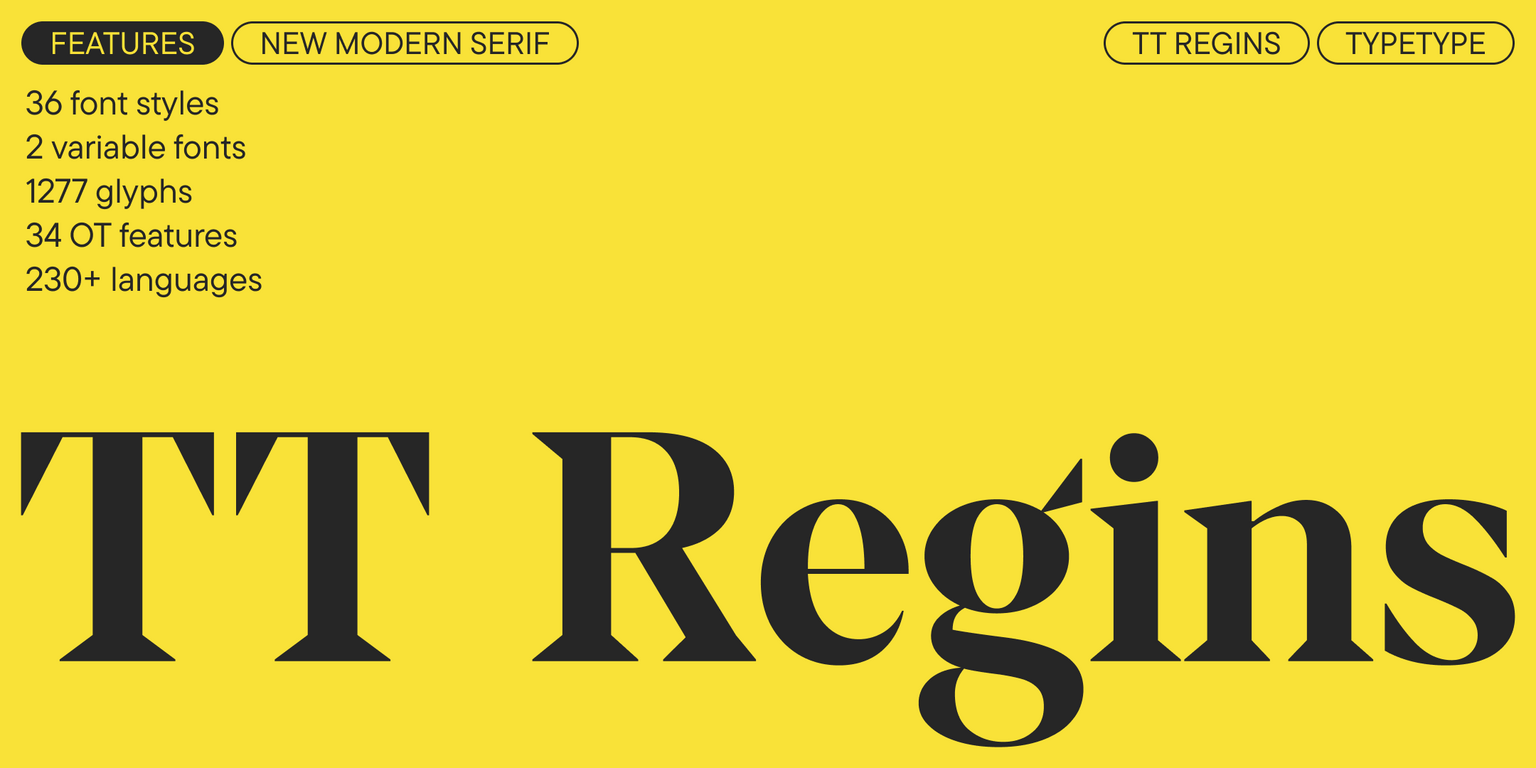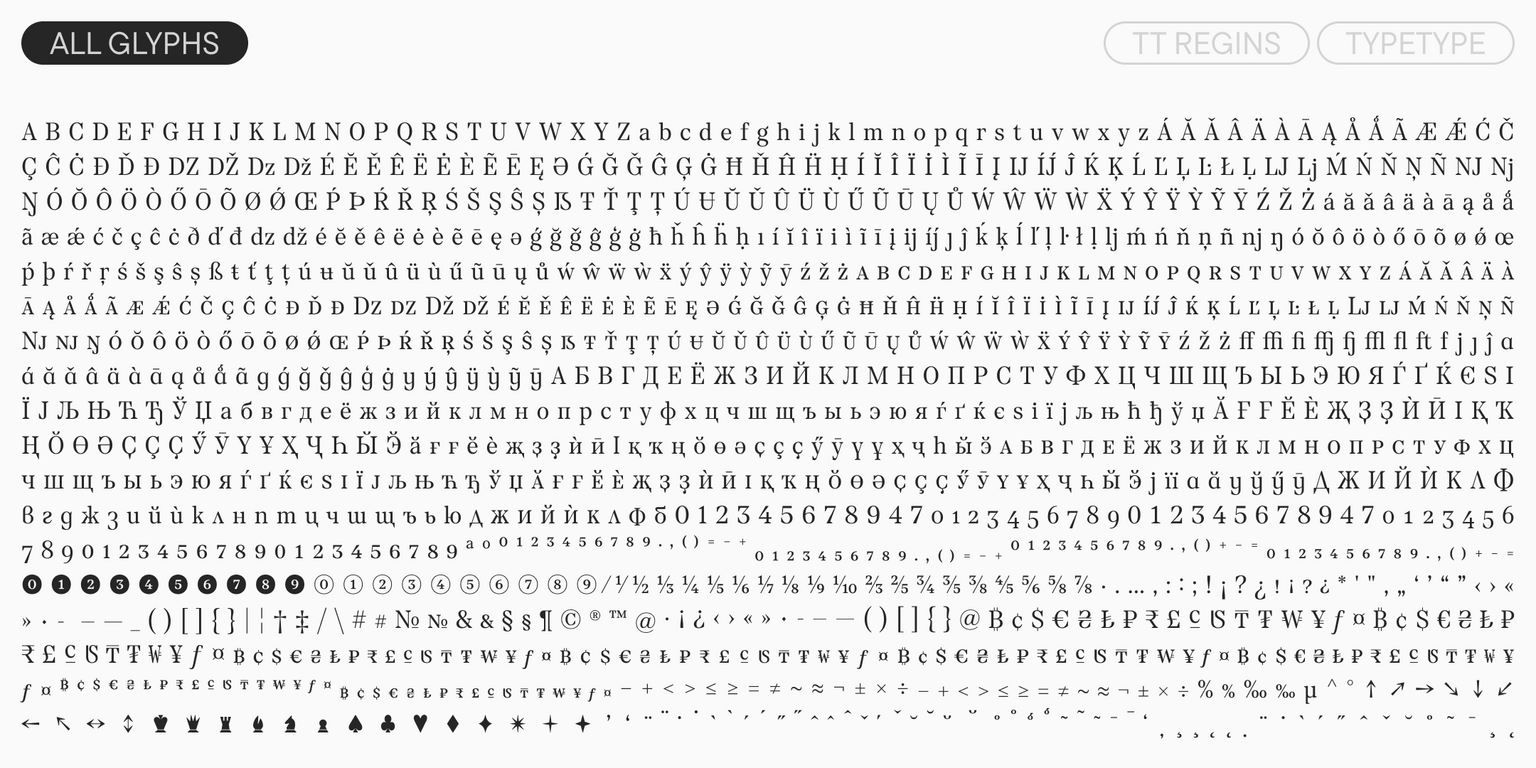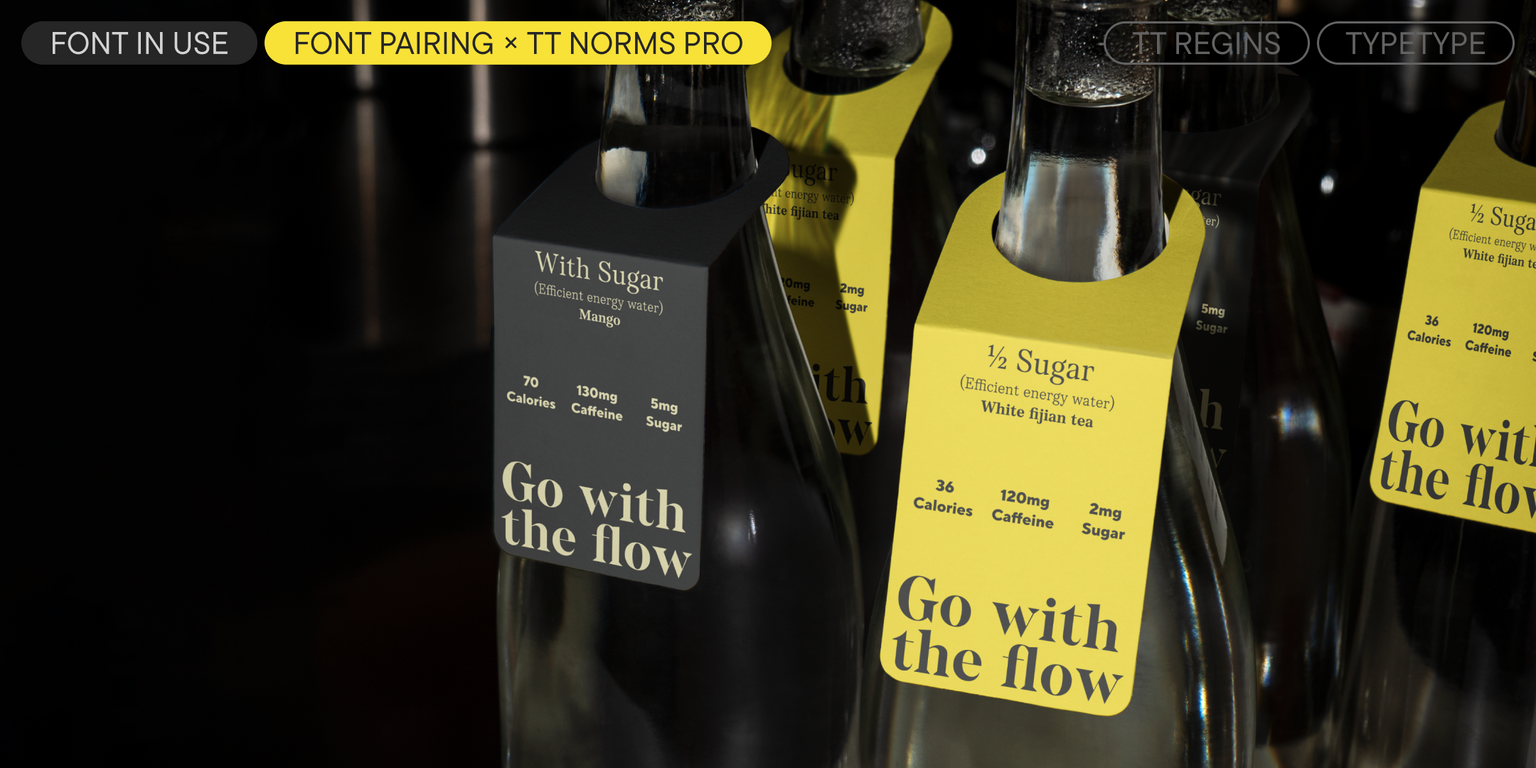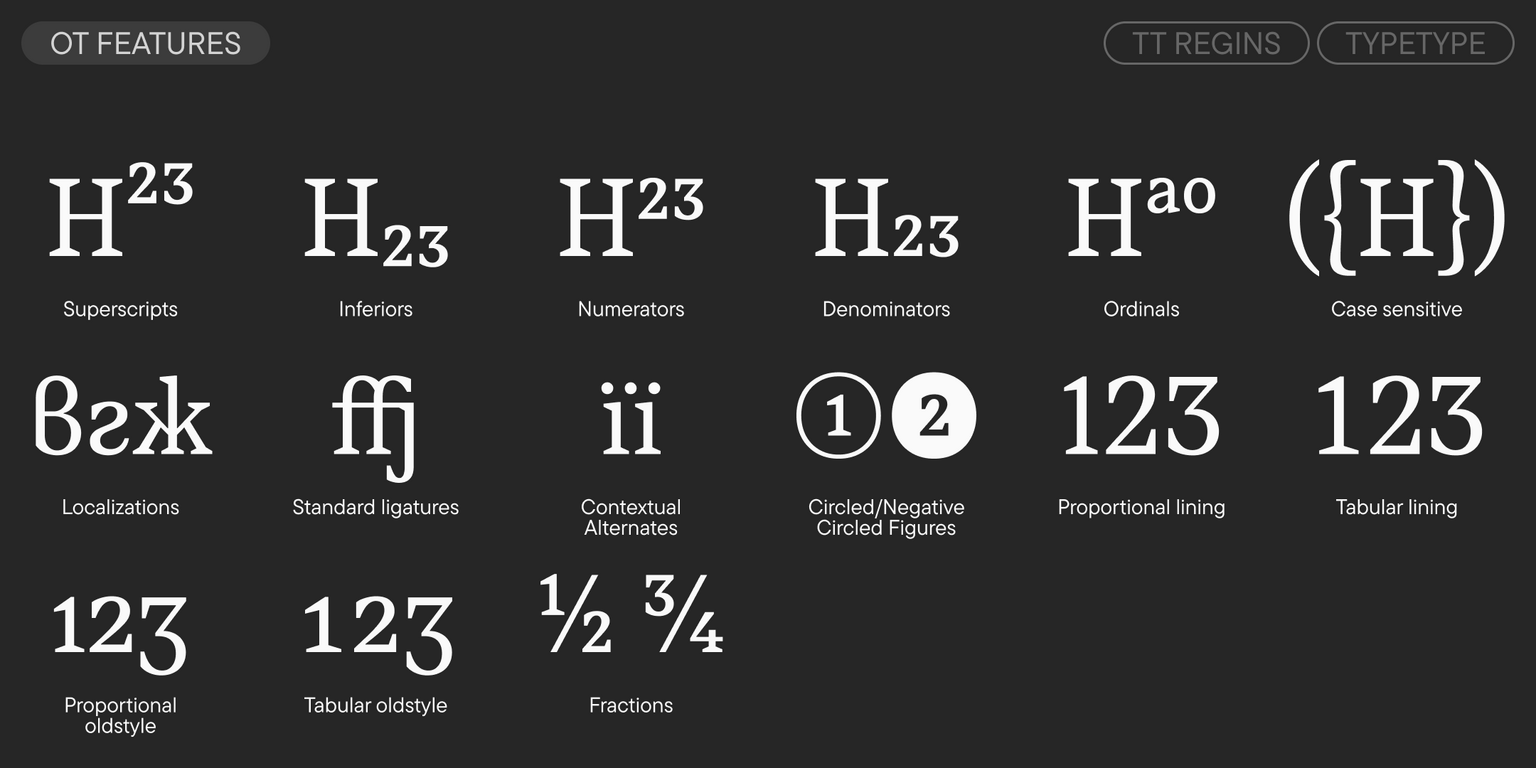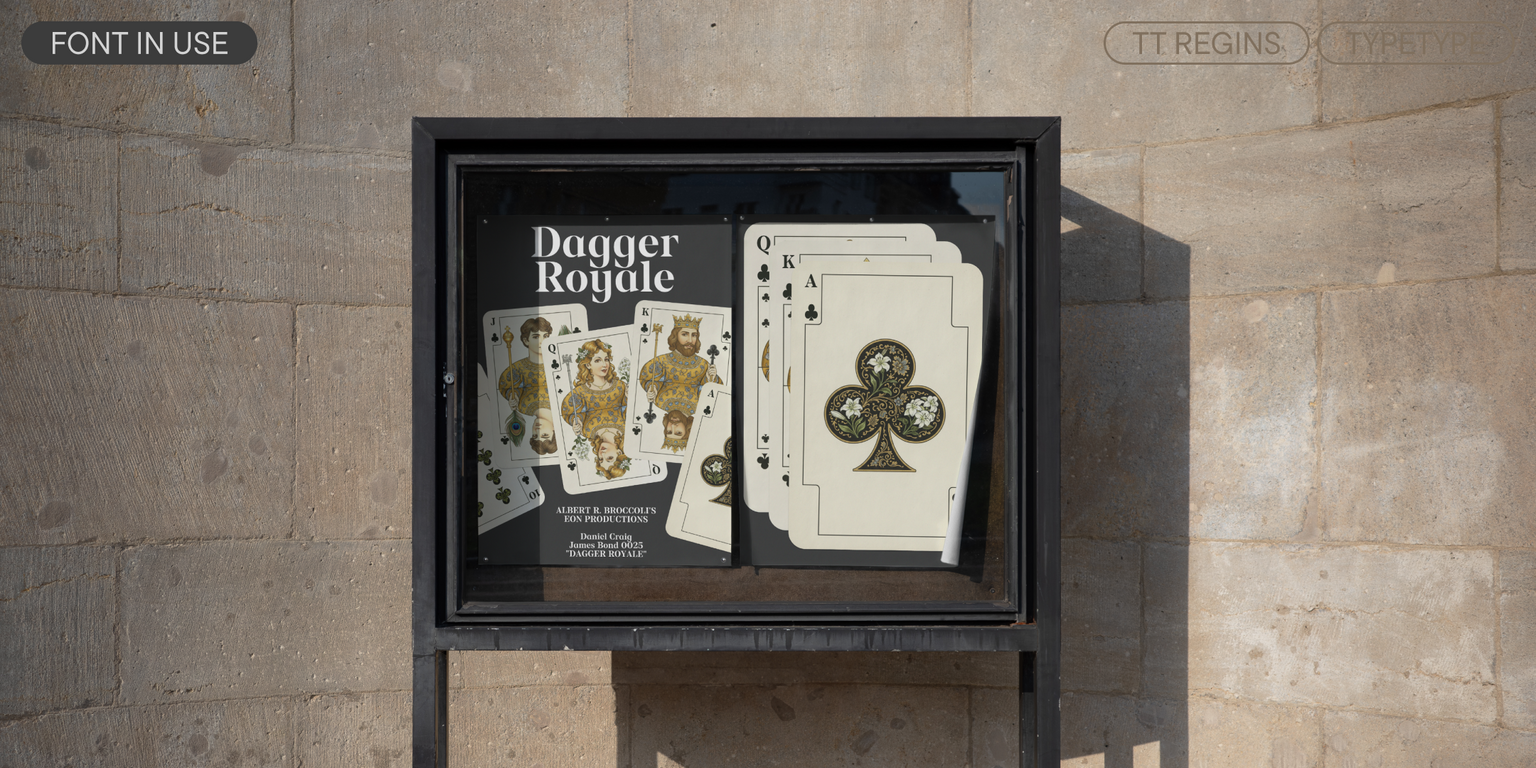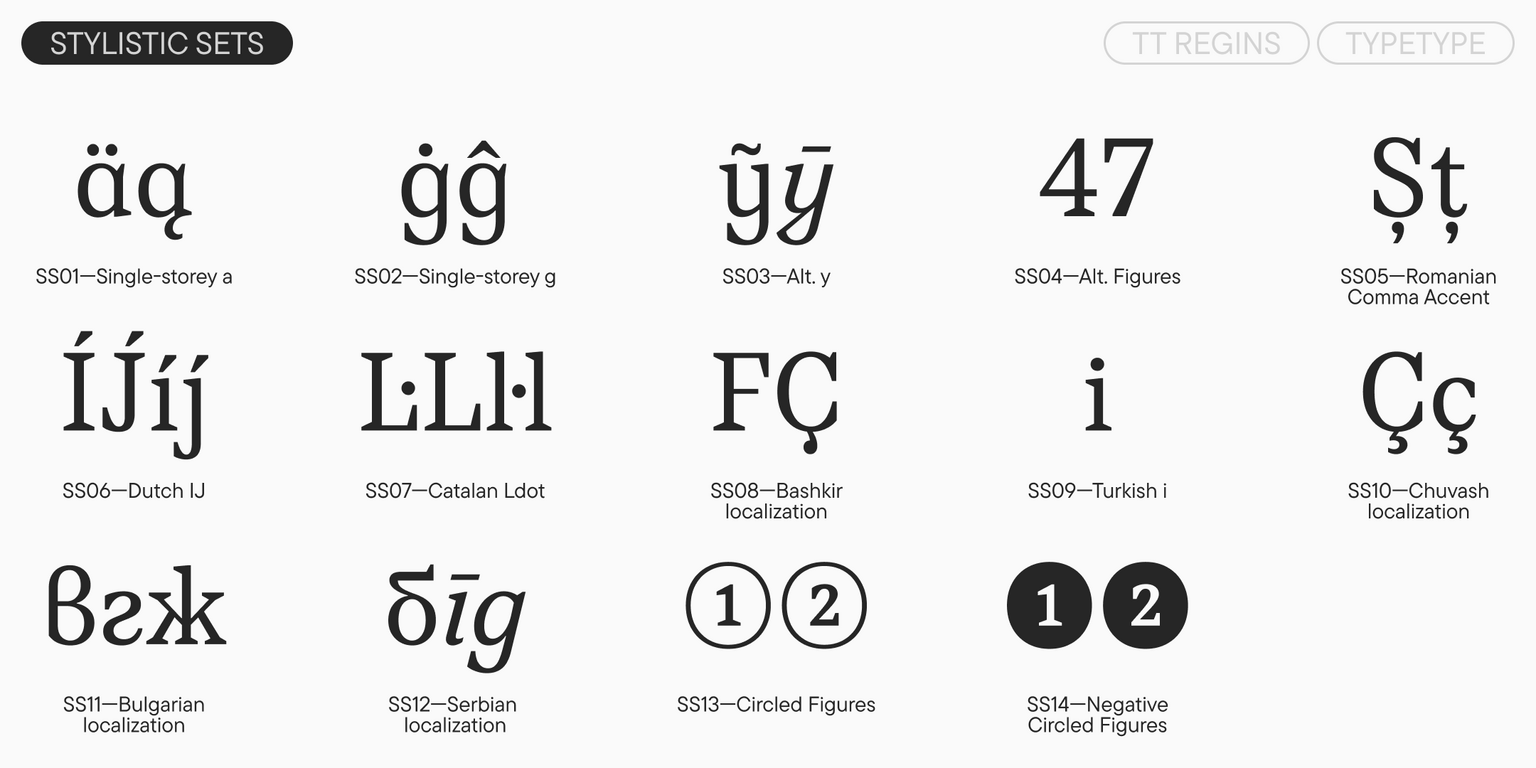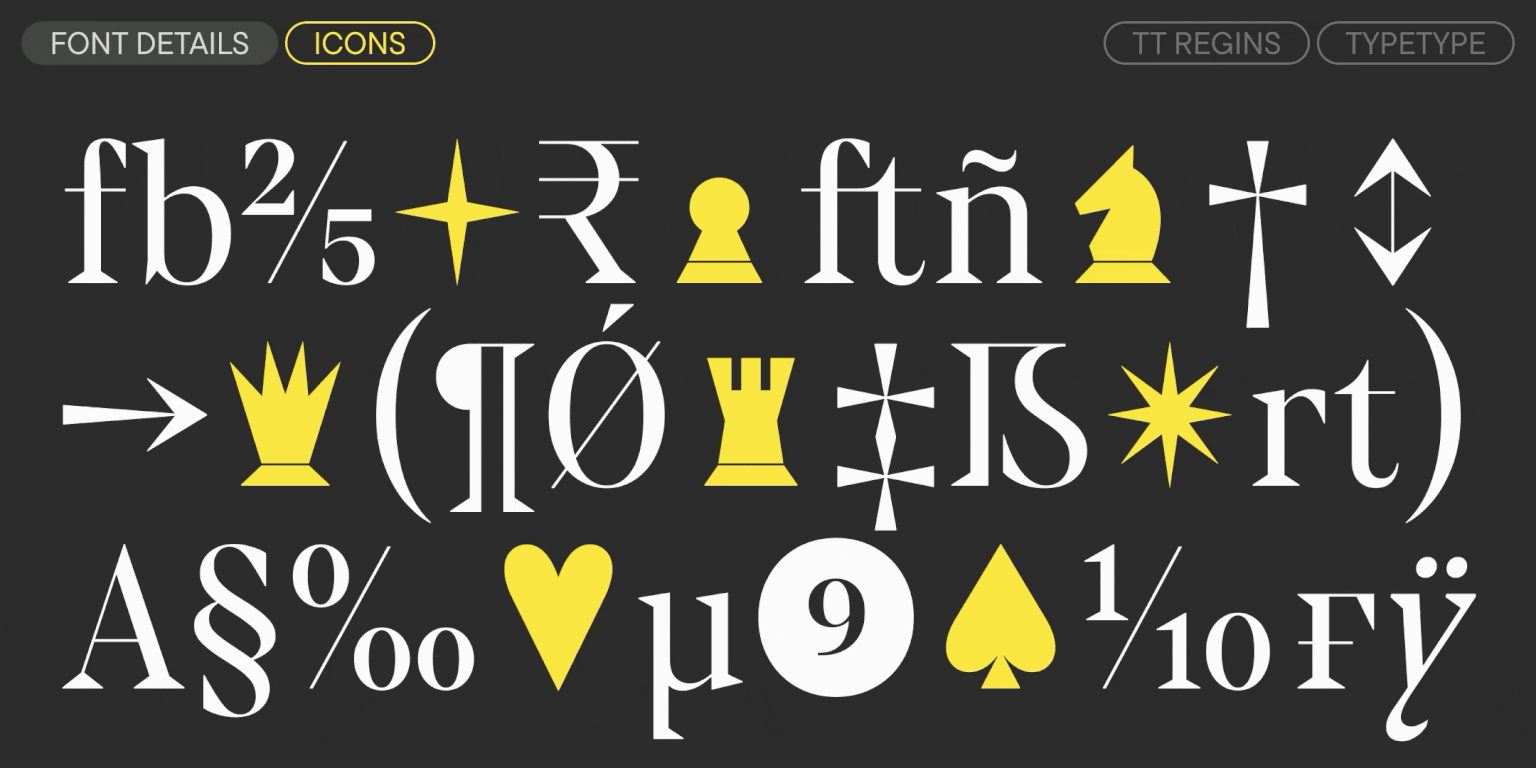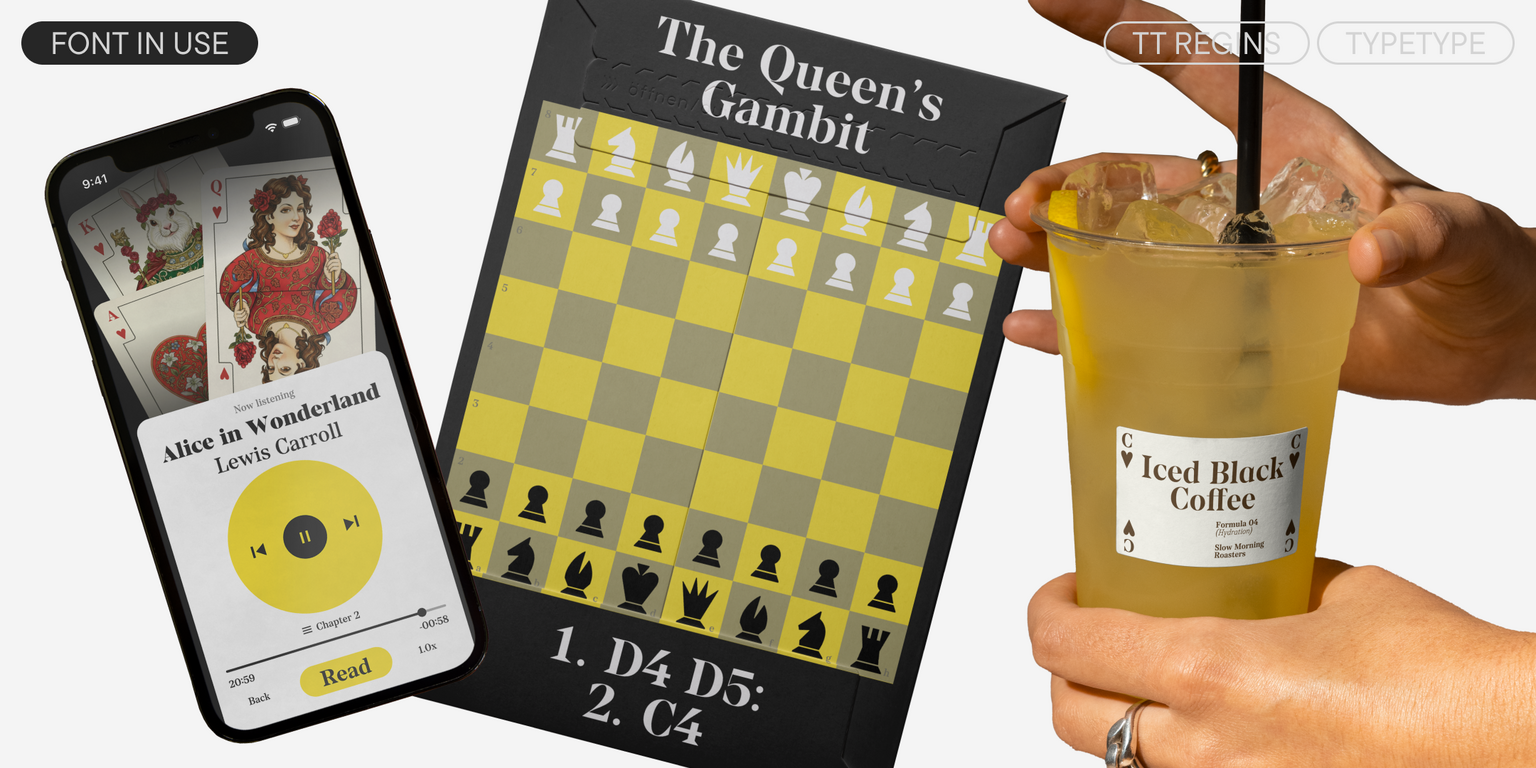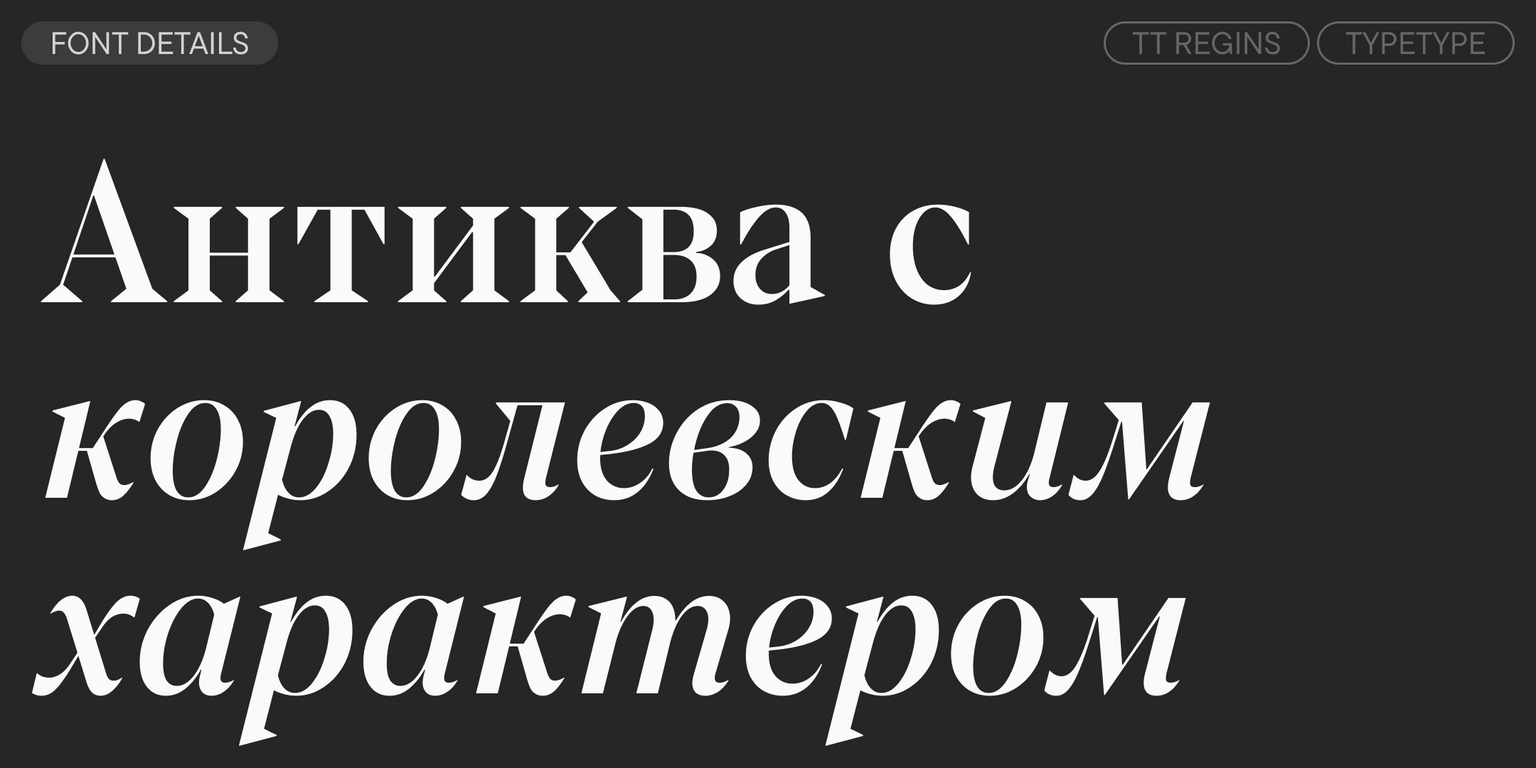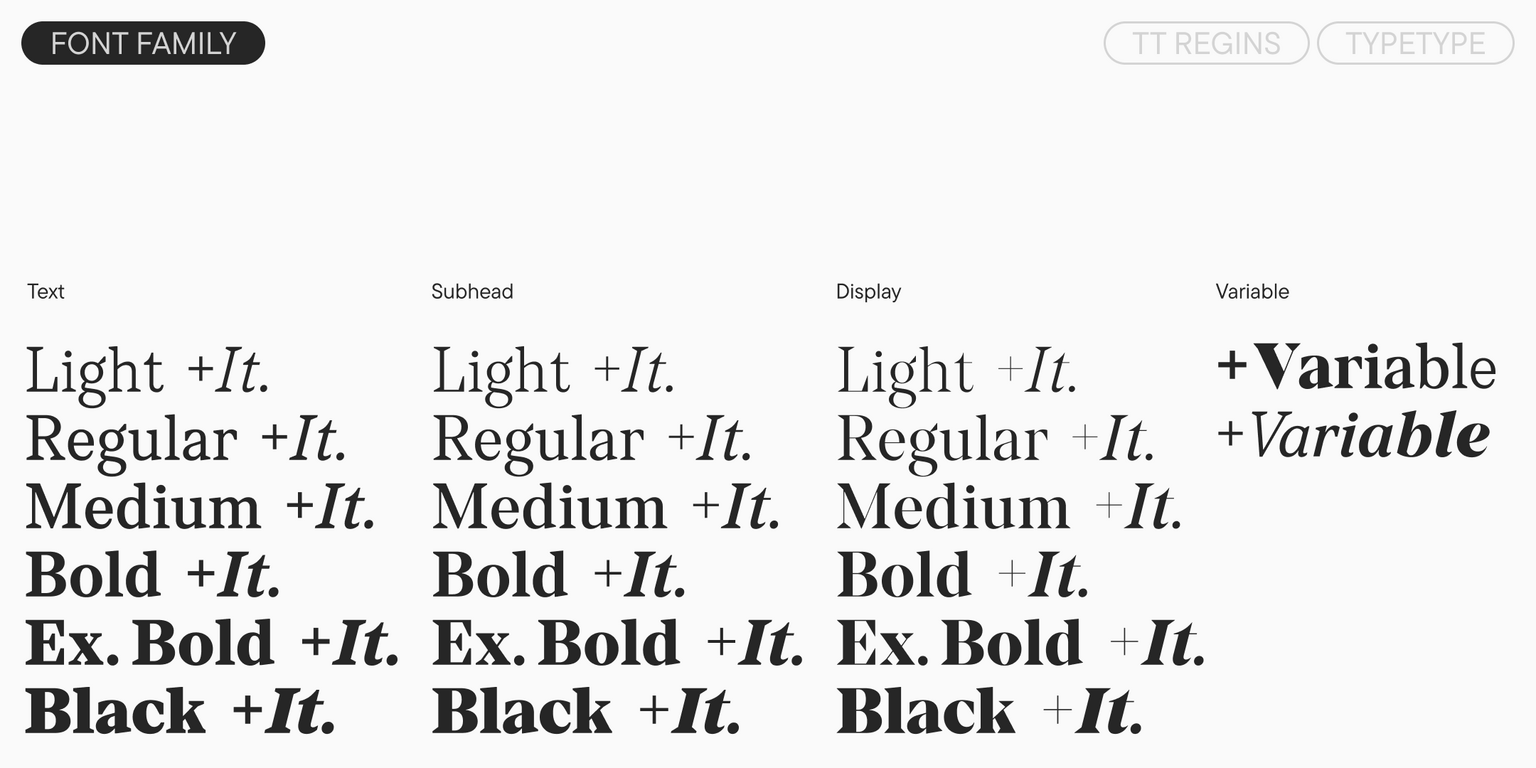
TT Regins
TT Regins — шотландская новостильная антиква с королевским характером. Яркий контраст и острые треугольные засечки придают этому шрифту строгий и властный нрав.
Встречайте новый TT Regins — шрифт с королевским характером!
TT Regins — шотландская новостильная антиква. Яркий контраст и острые треугольные засечки придают этому шрифту строгий и властный нрав, а точёные формы, укрупнённые строчные знаки и слегка зауженные равноширинные пропорции добавляют рисунку грациозности.
В TT Regins входит три подсемейства с разной степенью контрастности: Display, Text и промежуточное Subhead. В дисплейном подсемействе, предназначенном для крупных надписей, контраст наиболее выражен, и характер проявляется максимально ярко. В Text контраст приглушен для улучшения читаемости, чтобы шрифт безупречно работал в текстовом наборе. А Subhead можно использовать для акцентов и заголовков. Каждое начертание оптимизировано для комфортной работы в соответствующем диапазоне кеглей: ось оптических размеров позволяет адаптировать контраст и графику.
Особое внимание мы уделили курсиву, который получился ярким и динамичным. Он наклонён на 14° и очень выделяется в тексте за счёт «тру форм». Засечки сверху остаются острыми, а внизу становятся полукруглыми — это создаёт эффект скольжения и единого движения внутри текста.
В TT Regins входят стилистические сеты, с помощью которых можно сделать характер шрифта более плавным. Также возможности работы с гарнитурой расширяют два вариативных шрифта для работы с разным весом и кеглем в прямых и наклонных начертаниях. А ещё мы добавили атмосферный сет иконок на тему шахмат и игральных карт.
TT Regins очень универсален и функционален: разные начертания можно использовать для разных задач, создавая шрифтовые пары внутри одной гарнитуры. Он будет гармонично смотреться в модных журналах, в айдентике музеев и культурных институций, на упаковках духов, в оформлении исторических выставок. С его помощью легко создать ощущение элитарности и утончённости.
В TT Regins входит:
• 38 начертаний: 18 прямых, 18 наклонных и 2 вариативных шрифта;
• 1277 знаков в прямых начертаниях, 1285 — в италиках;
Главное правило, которому стоит следовать при создании шрифтовой пары — между двумя шрифтами должны четко прослеживаться как сходства, так и различия. Единство шрифтов можно подчеркнуть следующими характеристиками: контраст, пропорции, ширина, открытость знаков, формы отдельных букв и общий характер. Не бойтесь экспериментировать и пробовать разные сочетания. Анализируйте проекты, которые вам понравилиcь — так вы можете расширить свой визуальный опыт, повысить уровень знаний и уверенности при работе с типографикой.